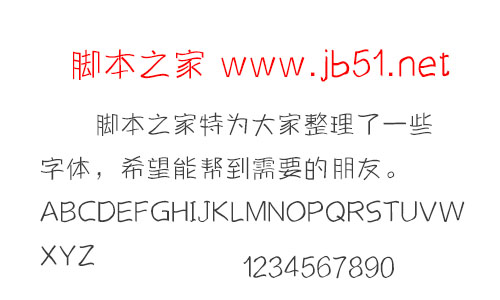
幾何波浪體是一款非常不錯(cuò)的藝術(shù)字體,工整簡(jiǎn)潔,具有強(qiáng)烈的視覺(jué)沖擊力,適應(yīng)于報(bào)紙和雜志和書(shū)籍中常用字體, 海報(bào)、個(gè)性促進(jìn)品牌標(biāo)志設(shè)計(jì)、字體設(shè)計(jì)、等環(huán)境使用,歡迎喜歡幾何波浪體的朋友前來(lái)下載使用。